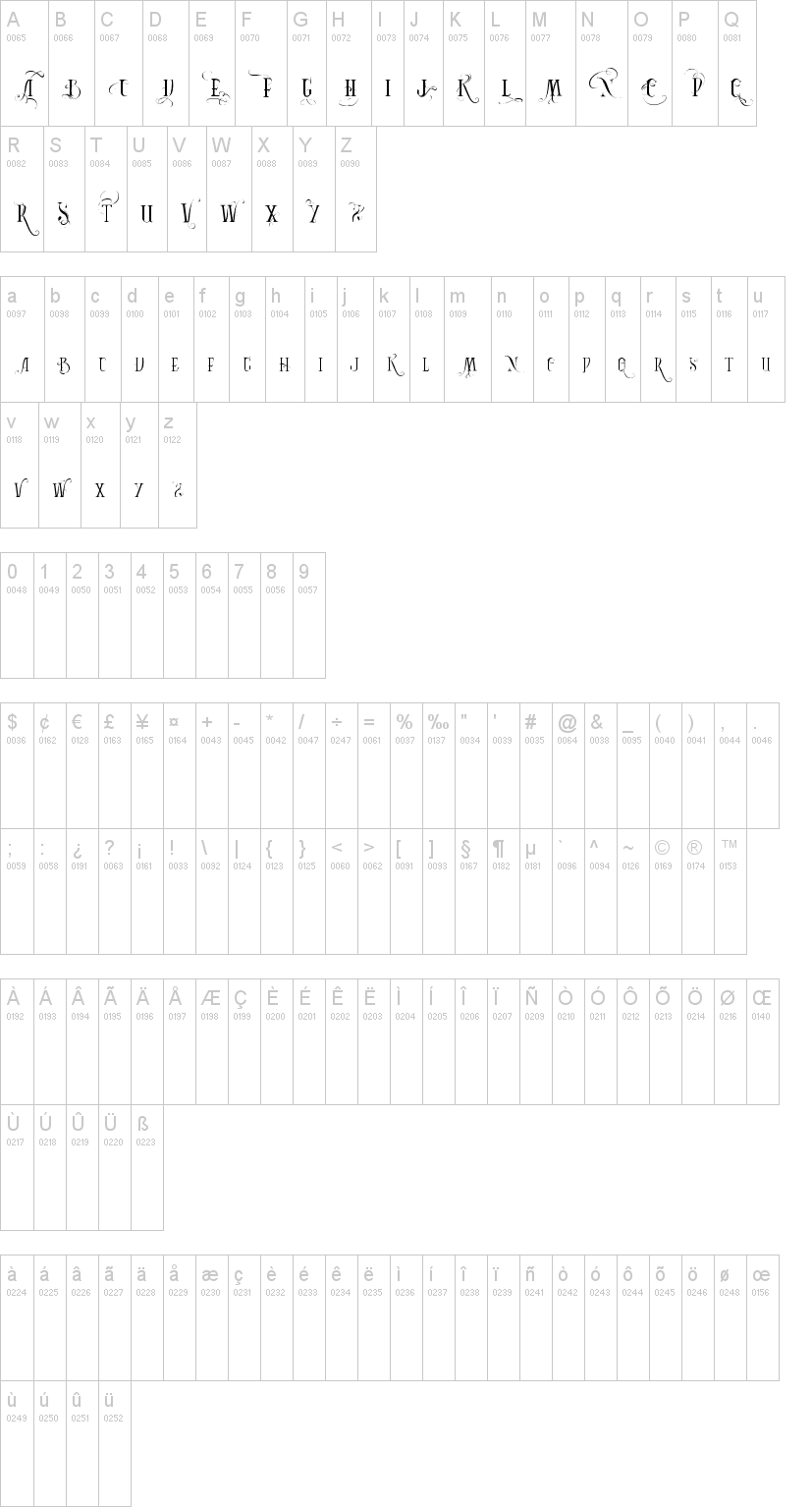
Vtks Bandoleones
? Vtks Bandoleones 是一款拉丁美洲风格的手写字体,它具有轻松愉悦的气息,更具有拉丁美洲风情。字体采用了拉丁美洲传统手写字体的笔画,拥有明显的曲线,更具有流动性,具有自然的手写风格。它可以用于标题、标签、卡片、海报等,为您的设计增添一份独特的魅力。
Vtks Bandoleones是一款非常不错的手写艺术字体,具有很好的视觉感,适合于文化类的宣传设计、商业类品牌的广告和产品包装设计以及个性化文字排版等较多场景。